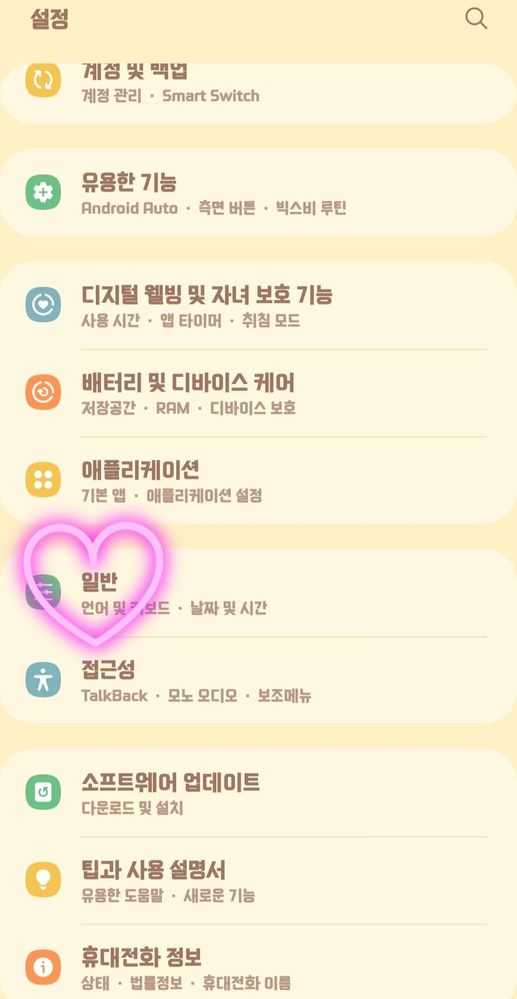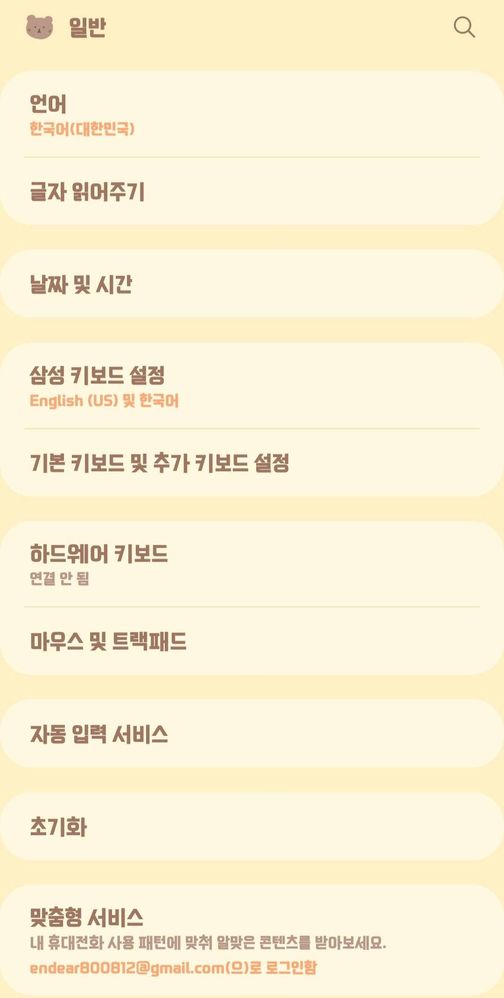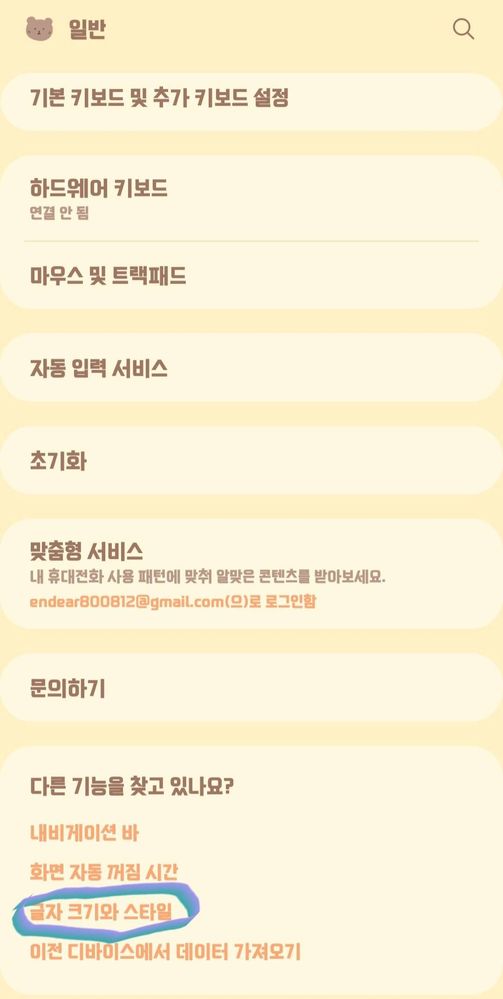
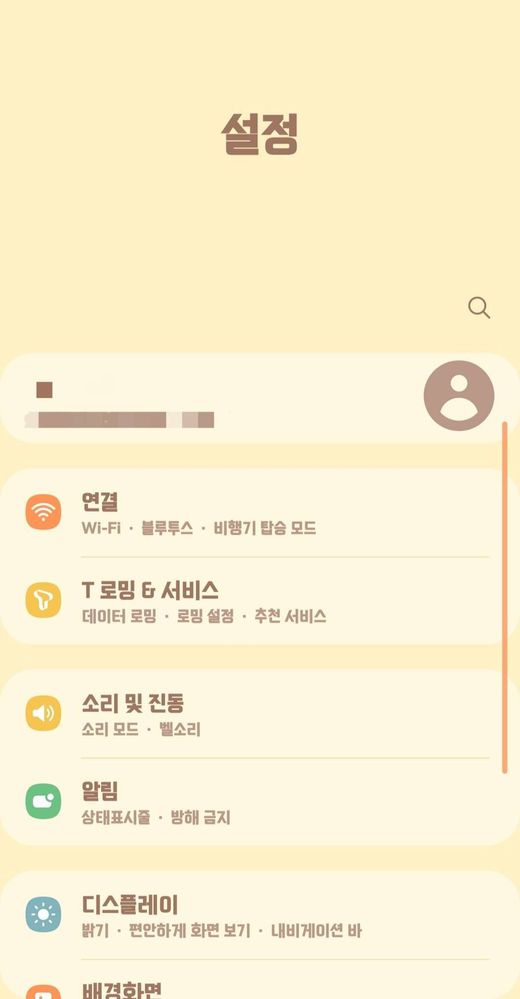
그러면 "글꼴"을 눌러줍니다. 저는 "GalaxyGamePlays한국어"로 글꼴을 정했어요.
처음에는 원래 기본, SamsungOne, 굵은 고딕 만 있어요.
귀엽고 아기자기한 손글씨체를 원하신다면 "산돌 미생체" 가 좋을것같아요. 조금 딱딱한 글씨체를 원하신다면 "나눔 명조", "애플 민트" 가 좋을것 같아요.